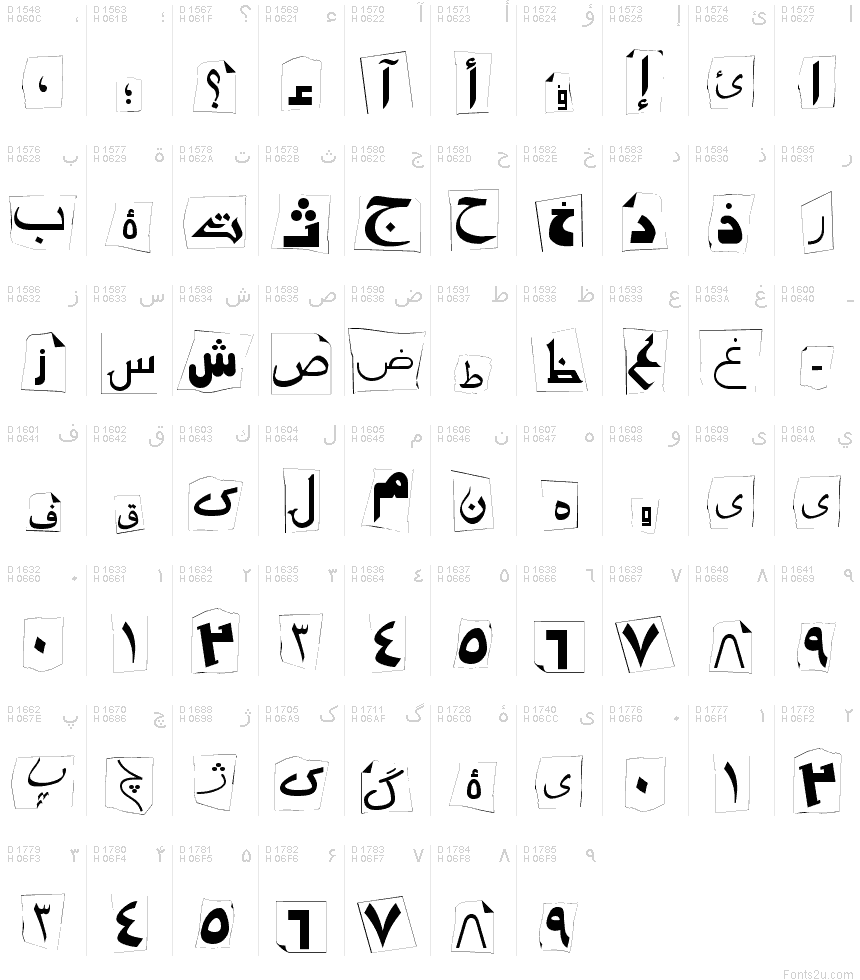
B Kidnap di Borna Rayaneh è un font display arabo gratuito, caratterizzato da linee angolari e un’estetica essenziale che ricorda il ritaglio di carta. Le lettere appaiono pesanti, compatte e geometricamente nette, bilanciando forme esterne decise con piccole aperture intagliate che conferiscono al design un ritmo teso, quasi da poster.
È la scelta ideale per flyer musicali, grafiche streetwear, titoli, zine e progetti di branding compatti che richiedono un font gratuito con una personalità araba decisa. Funziona al meglio in testi brevi e d’impatto – copertine, loghi e titoli rapidi – poiché le forme dense e gli angoli netti donano anche alle frasi più brevi una presenza grafica solida e definita.